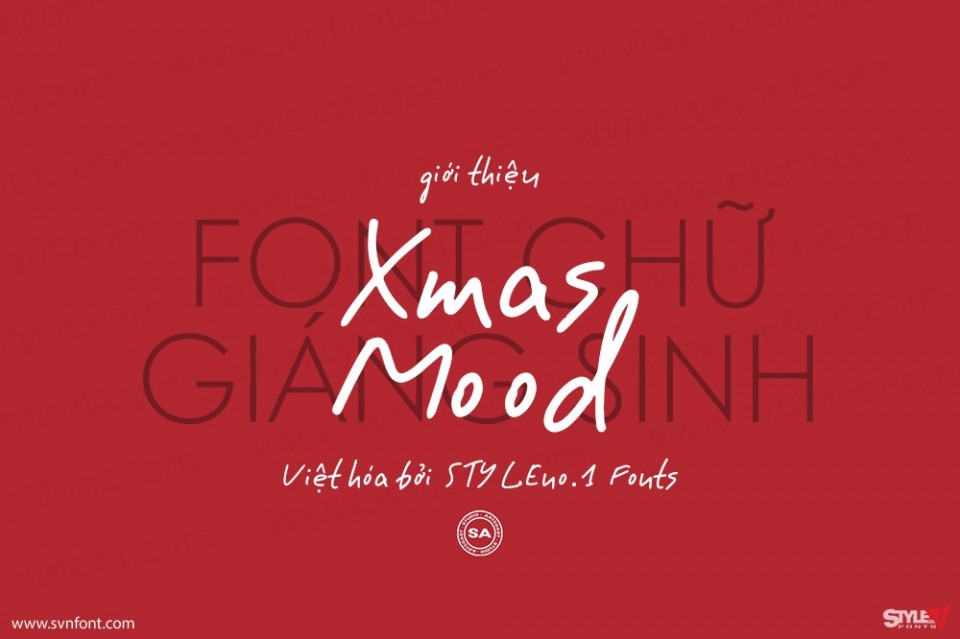
Font việt hóa SVN SA Xmas Mood giáng sinh
Giới thiệu về Font việt hóa SVN SA Xmas Mood giáng sinh
Mùa lễ hội cuối năm đang đến gần, nhu cầu tìm kiếm các mẫu Font Miễn Phí mang đậm không khí lễ hội ngày càng tăng cao. Trong đó, Font việt hóa SVN SA Xmas Mood giáng sinh nổi lên như một lựa chọn hàng đầu cho các nhà thiết kế tại Việt Nam. Đây là bộ phông chữ được tinh chỉnh kỹ lưỡng về dấu tiếng Việt, giúp bạn dễ dàng truyền tải thông điệp ấm áp và an lành thông qua các ấn phẩm truyền thông chuyên nghiệp.
Đặc điểm nổi bật của font chữ
Bộ font này sở hữu những đường nét uốn lượn mềm mại, mô phỏng phong cách viết tay đầy nghệ thuật. Những chi tiết nhỏ trong chữ cái gợi lên hình ảnh của những bông tuyết, dải ruy băng và ánh đèn lung linh. Việc sử dụng Font việt hóa SVN SA Xmas Mood giáng sinh giúp các em học sinh và thầy cô tạo ra những tấm thiệp chúc mừng hoặc bài thuyết trình sinh động, mang lại cảm giác gần gũi và thân thiện trong môi trường học đường.
Ứng dụng Font việt hóa SVN SA Xmas Mood giáng sinh trong thiết kế
Sáng tạo thiệp và banner sự kiện
Với phong cách trình bày độc đáo, bộ chữ này cực kỳ phù hợp để thiết kế tiêu đề cho các biểu ngữ chào đón Noel tại trường học hoặc trang trí bảng tin lớp. Độ tương phản cao và khả năng hiển thị rõ nét giúp người xem dễ dàng tiếp nhận nội dung dù ở khoảng cách xa. Bạn có thể kết hợp font chữ này với các tông màu đỏ, xanh lá và vàng kim để tạo nên sự hài hòa tuyệt đối cho thị giác.
Lưu ý khi sử dụng bộ font
Dù có thiết kế cầu kỳ, bạn nên ưu tiên sử dụng font cho các đoạn văn bản ngắn hoặc tiêu đề để đảm bảo tính thẩm mỹ cao nhất. Đối với các văn bản dài, hãy kết hợp với một font không chân đơn giản để tạo sự cân bằng. Cuối cùng, đừng quên tải ngay Font Miễn Phí, Font Việt Hóa, Font việt hóa SVN SA Xmas Mood giáng sinh để bắt đầu dự án sáng tạo của mình ngay hôm nay. Hy vọng bộ font này sẽ mang lại nguồn cảm hứng mới mẻ cho bạn.